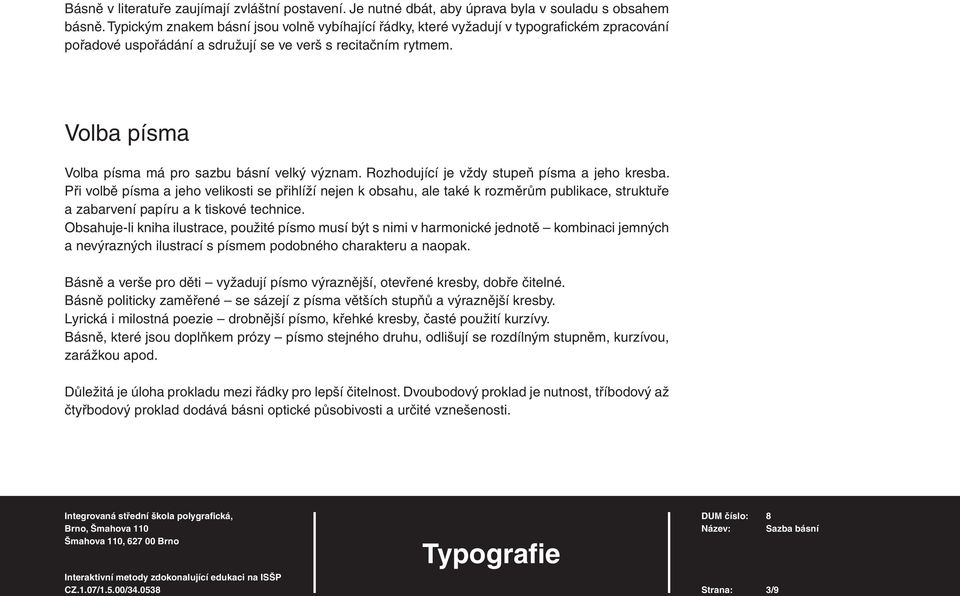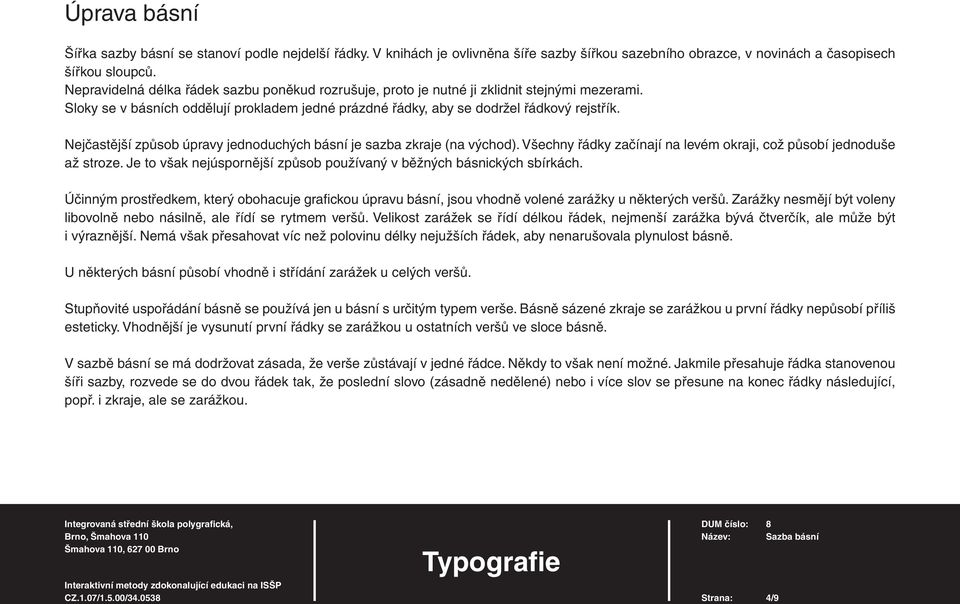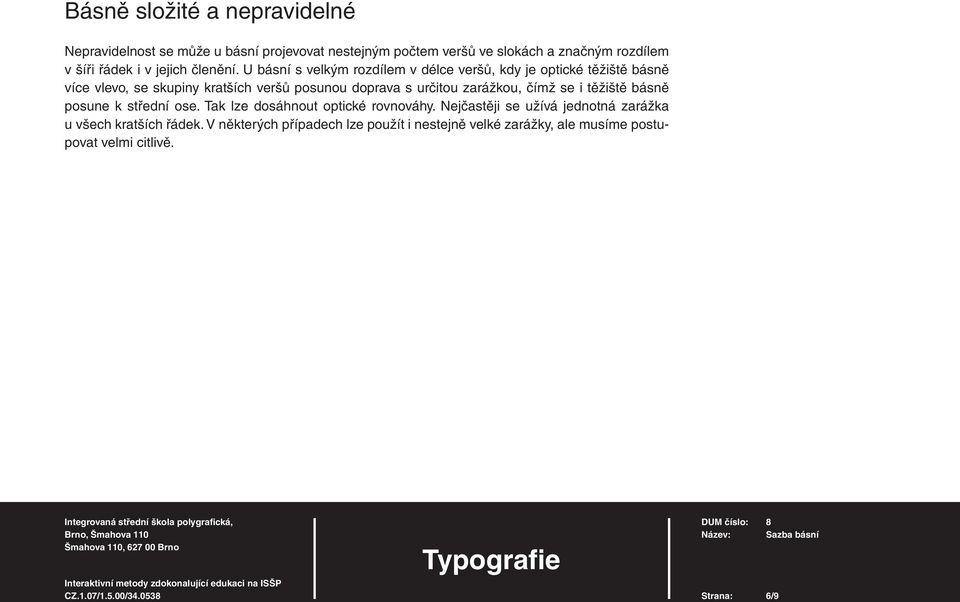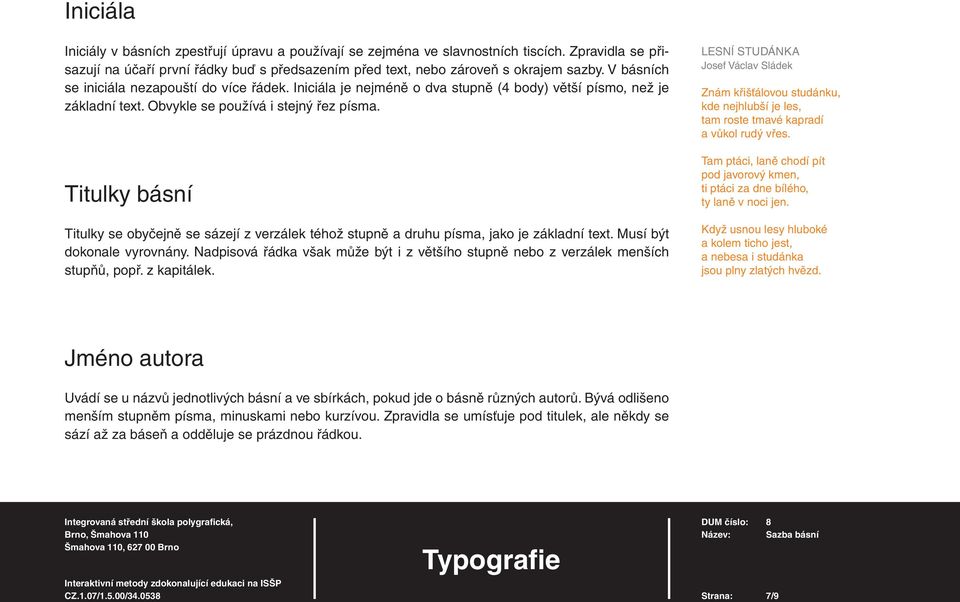
8. Sazba básní. Typografie
3 Básně v literatuře zaujímají zvláštní postavení. Je nutné dbát, aby úprava byla v souladu s obsahem básně. Typickým znakem básní jsou volně vybíhající řádky, které vyžadují v typografi ckém zpracování pořadové uspořádání a sdružují se ve verš s recitačním rytmem. Volba písma má pro sazbu básní velký význam. Rozhodující je vždy stupeň písma a jeho kresba. Při volbě písma a jeho velikosti se přihlíží nejen k obsahu, ale také k rozměrům publikace, struktuře a zabarvení papíru a k tiskové technice. Obsahuje-li kniha ilustrace, použité písmo musí být s nimi v harmonické jednotě kombinaci jemných a nevýrazných ilustrací s písmem podobného charakteru a naopak. Básně a verše pro děti vyžadují písmo výraznější, otevřené kresby, dobře čitelné. Básně politicky zaměřené se sázejí z písma větších stupňů a výraznější kresby. Lyrická i milostná poezie drobnější písmo, křehké kresby, časté použití kurzívy. Básně, které jsou doplňkem prózy písmo stejného druhu, odlišují se rozdílným stupněm, kurzívou, zarážkou apod. Důležitá je úloha prokladu mezi řádky pro lepší čitelnost. Dvoubodový proklad je nutnost, tříbodový až čtyřbodový proklad dodává básni optické působivosti a určité vznešenosti. Strana: 3/9
4 Úprava básní Šířka sazby básní se stanoví podle nejdelší řádky. V knihách je ovlivněna šíře sazby šířkou sazebního obrazce, v novinách a časopisech šířkou sloupců. Nepravidelná délka řádek sazbu poněkud rozrušuje, proto je nutné ji zklidnit stejnými mezerami. Sloky se v básních oddělují prokladem jedné prázdné řádky, aby se dodržel řádkový rejstřík. Nejčastější způsob úpravy jednoduchých básní je sazba zkraje (na východ). Všechny řádky začínají na levém okraji, což působí jednoduše až stroze. Je to však nejúspornější způsob používaný v běžných básnických sbírkách. Účinným prostředkem, který obohacuje grafi ckou úpravu básní, jsou vhodně volené zarážky u některých veršů. Zarážky nesmějí být voleny libovolně nebo násilně, ale řídí se rytmem veršů. Velikost zarážek se řídí délkou řádek, nejmenší zarážka bývá čtverčík, ale může být i výraznější. Nemá však přesahovat víc než polovinu délky nejužších řádek, aby nenarušovala plynulost básně. U některých básní působí vhodně i střídání zarážek u celých veršů. Stupňovité uspořádání básně se používá jen u básní s určitým typem verše. Básně sázené zkraje se zarážkou u první řádky nepůsobí příliš esteticky. Vhodnější je vysunutí první řádky se zarážkou u ostatních veršů ve sloce básně. V sazbě básní se má dodržovat zásada, že verše zůstávají v jedné řádce. Někdy to však není možné. Jakmile přesahuje řádka stanovenou šíři sazby, rozvede se do dvou řádek tak, že poslední slovo (zásadně nedělené) nebo i více slov se přesune na konec řádky následující, popř. i zkraje, ale se zarážkou. Strana: 4/9
5 Sazba zkraje Zarážka volena s přihlédnutím k rytmu veršů. Odsazení první řádky Stupňovitá zarážka Střídavé odsazení První řádek předsazený Střídání zarážek u celých veršů Strana: 5/9
6 Básně složité a nepravidelné Nepravidelnost se může u básní projevovat nestejným počtem veršů ve slokách a značným rozdílem v šíři řádek i v jejich členění. U básní s velkým rozdílem v délce veršů, kdy je optické těžiště básně více vlevo, se skupiny kratších veršů posunou doprava s určitou zarážkou, čímž se i těžiště básně posune k střední ose. Tak lze dosáhnout optické rovnováhy. Nejčastěji se užívá jednotná zarážka u všech kratších řádek. V některých případech lze použít i nestejně velké zarážky, ale musíme postupovat velmi citlivě. Strana: 6/9
7 Iniciála Iniciály v básních zpestřují úpravu a používají se zejména ve slavnostních tiscích. Zpravidla se přisazují na účaří první řádky buď s předsazením před text, nebo zároveň s okrajem sazby. V básních se iniciála nezapouští do více řádek. Iniciála je nejméně o dva stupně (4 body) větší písmo, než je základní text. Obvykle se používá i stejný řez písma. Titulky básní Titulky se obyčejně se sázejí z verzálek téhož stupně a druhu písma, jako je základní text. Musí být dokonale vyrovnány. Nadpisová řádka však může být i z většího stupně nebo z verzálek menších stupňů, popř. z kapitálek. LESNÍ STUDÁNKA Josef Václav Sládek Jméno autora Uvádí se u názvů jednotlivých básní a ve sbírkách, pokud jde o básně různých autorů. Bývá odlišeno menším stupněm písma, minuskami nebo kurzívou. Zpravidla se umísťuje pod titulek, ale někdy se sází až za báseň a odděluje se prázdnou řádkou. Strana: 7/9